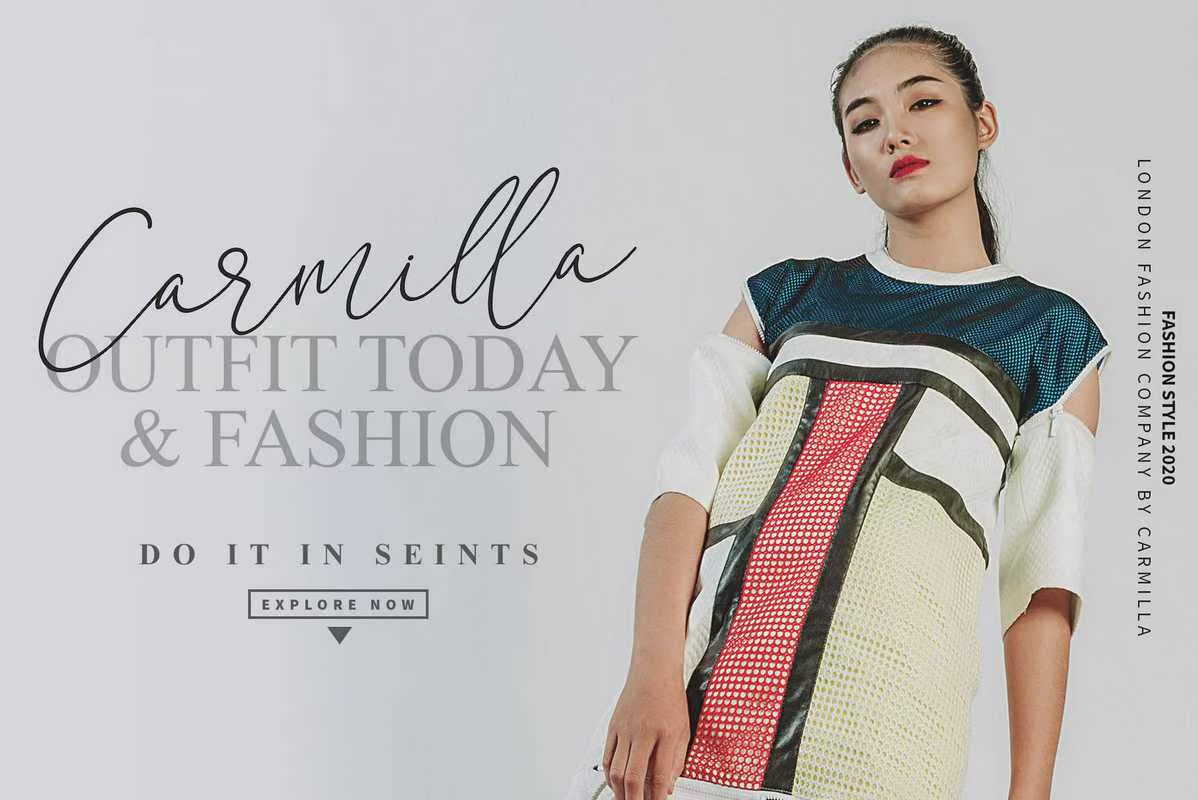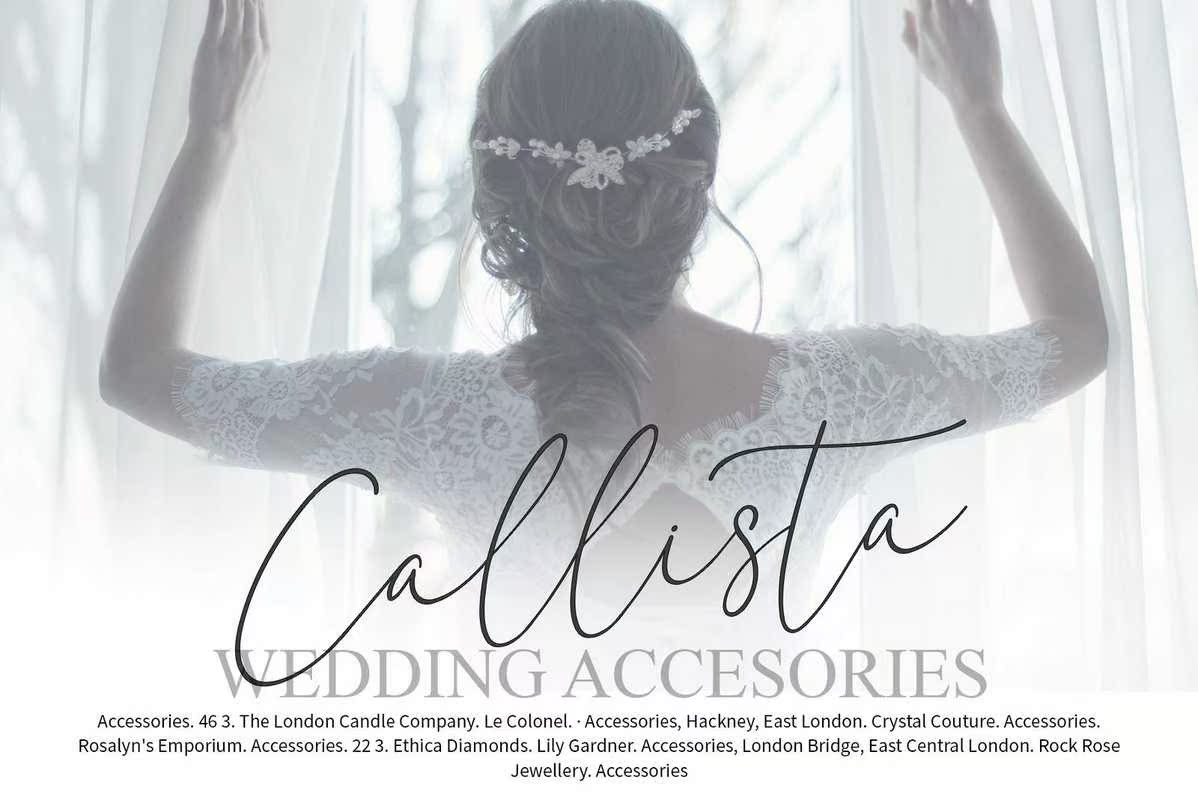
CalistinScriptTypeface.适合您的项目的文字和数字集合非常适合于标识、品牌设计、标识设计、数字刻字艺术、T恤/服装、海报、杂志、标志、广告设计和任何设计需求。CalistinScriptTypeface.适合您的项目的文字和数字集合非常适合于标识、品牌设计、标识设计,数字文字艺术、T恤/服装、海报、杂志、标志、广告设计和任何设计需求。